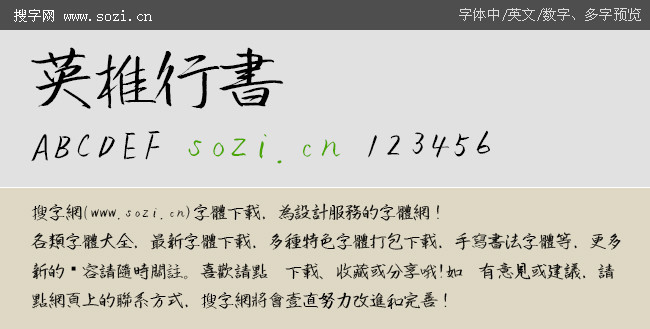
英椎行書(shū)
搜字網(wǎng)給大家提供一款英椎行書(shū)中文字體下載,英椎行書(shū)字體端莊雄偉,書(shū)寫(xiě)工整,是一款十分好看的手寫(xiě)字體。共收錄了6879個(gè)文字,繁體字支持得比較完整。簡(jiǎn)體字?jǐn)?shù)相對(duì)較少,不過(guò)也確實(shí)是一款難得的字體。